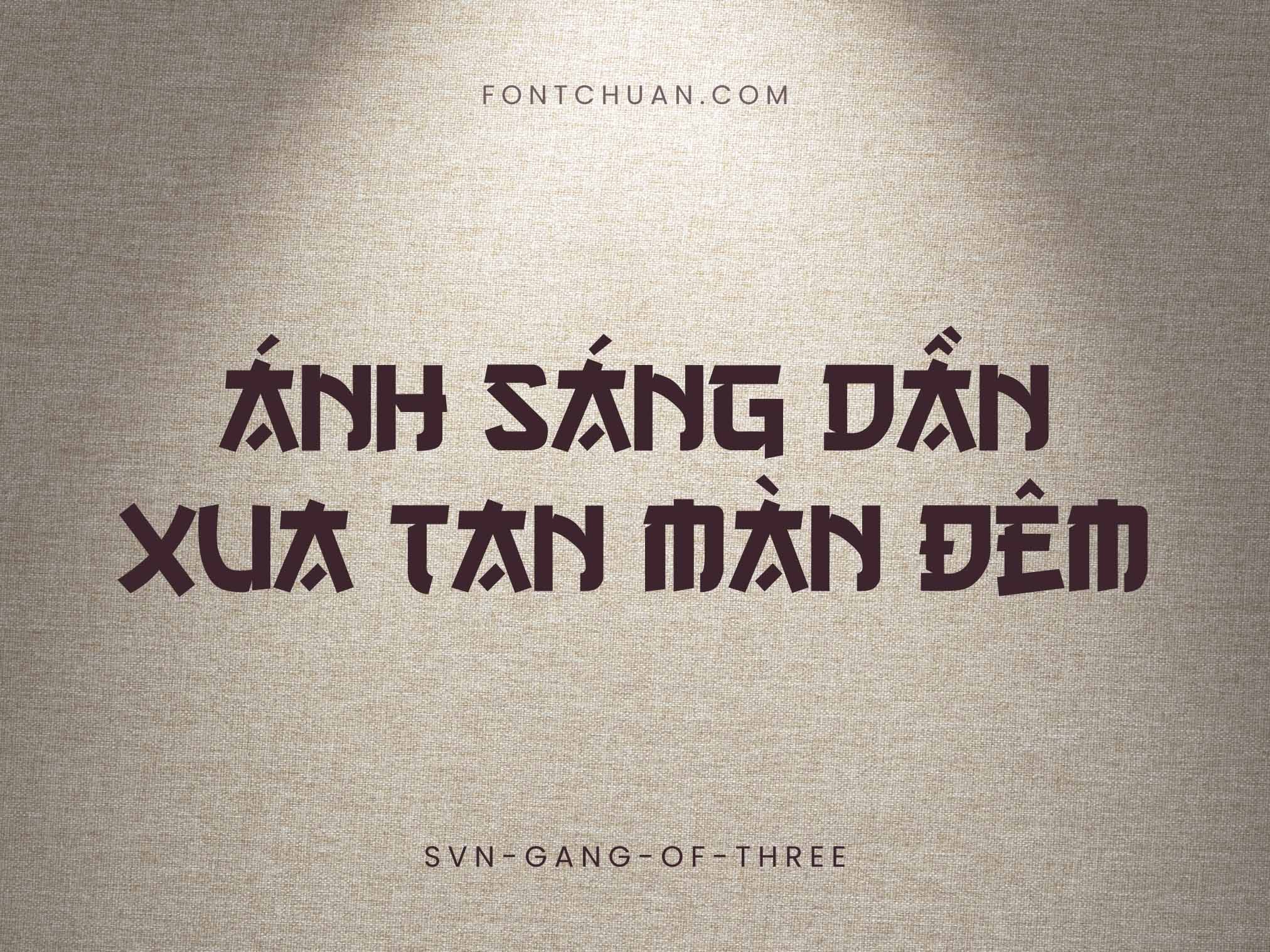
Font SVN Gang Of Three Việt Hóa
Font SVN Gang of Three là phiên bản Việt hóa của kiểu chữ Gang of Three, được thực hiện bởi Styleno.1 Fonts. Gang of Three là một kiểu chữ mang phong cách Nhật Bản, nổi bật với các đường nét góc cạnh và mạnh mẽ, tạo cảm giác độc đáo và ấn tượng. Với thiết kế táo bạo và hình khối đặc trưng, SVN Gang of Three cũng có thể được sử dụng như một Font chữ Halloween, giúp mang lại không khí huyền bí, lạ mắt và năng động cho các thiết kế chủ đề lễ hội. Font này đã được sử dụng trong tựa game nổi tiếng “Fruit Ninja”, góp phần tạo nên sự hấp dẫn về mặt thị giác cho trò chơi.
SVN Gang of Three lý tưởng cho các dự án thiết kế yêu cầu sự độc đáo và nổi bật, như thiết kế logo, tiêu đề, bao bì sản phẩm và các ấn phẩm quảng cáo. Các ngành nghề như quảng cáo và công nghệ có thể tận dụng font này để tạo điểm nhấn trong thiết kế. Ngoài ra, font cũng thích hợp cho các sự kiện như Halloween, Tết và các lễ hội khác.